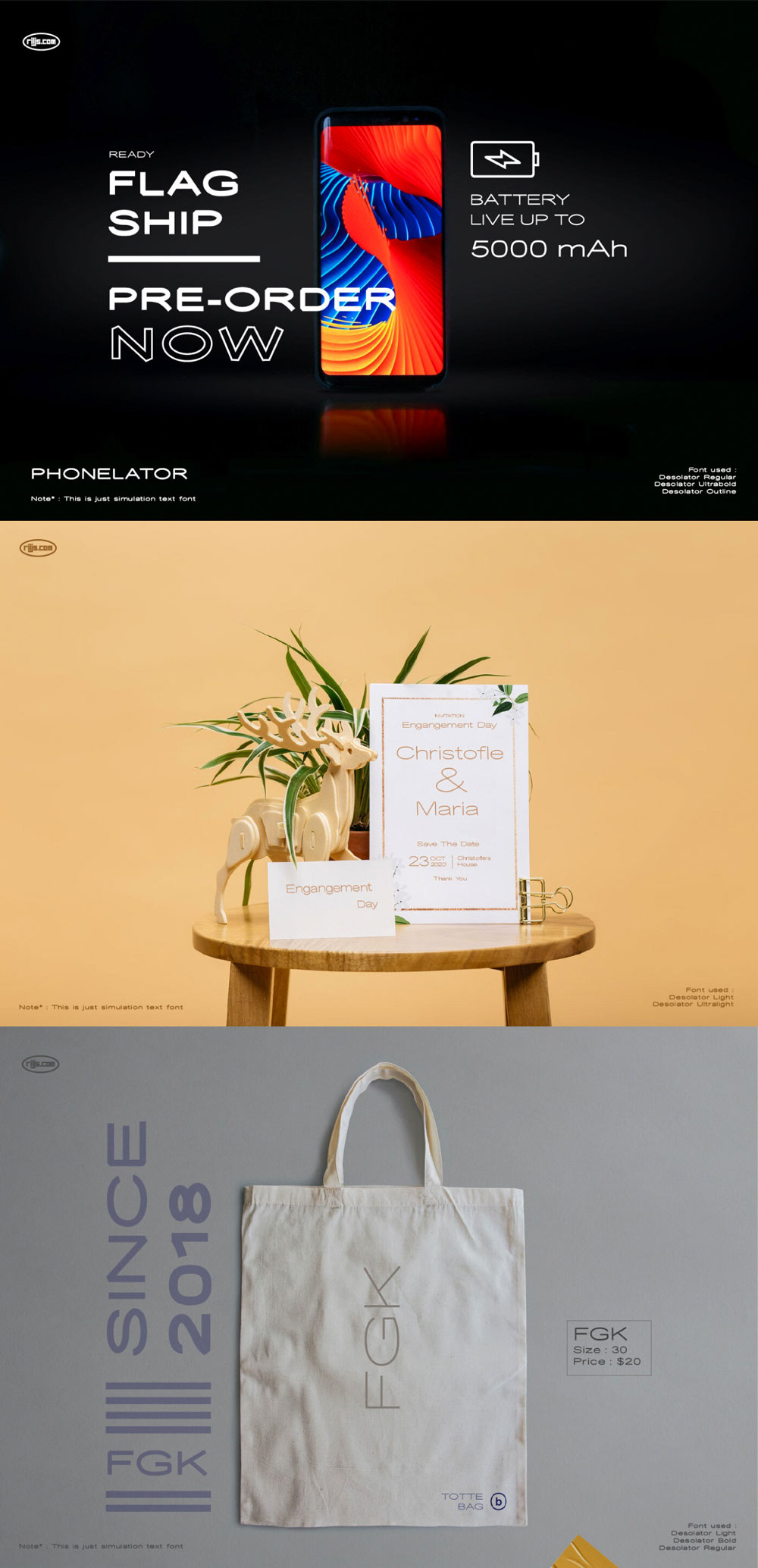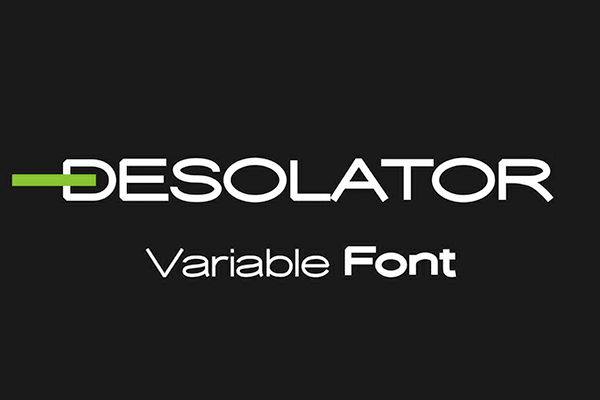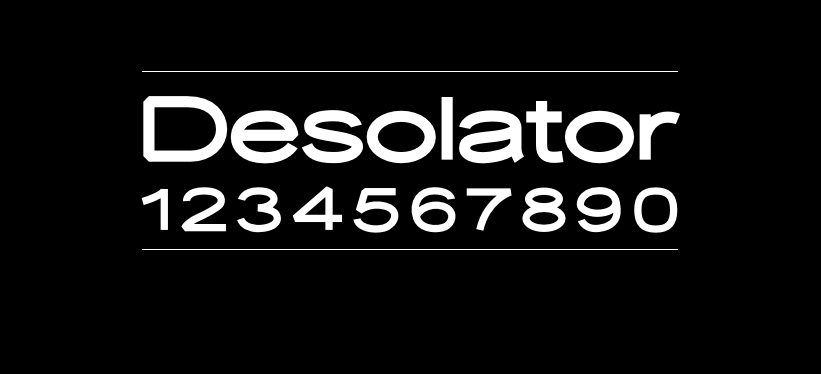
Desolator
Desolator字体介绍
Desolator是Ril Js Anwar创建的新字体 , 是一款支持多字重的现代Sans Serif,具有尖锐的角度和微妙的曲线。Desolator字体字形稳重大气,包含3字重,适合LOGO、标题、海报等场合,个人及商用免费
Desolator字体应用示例